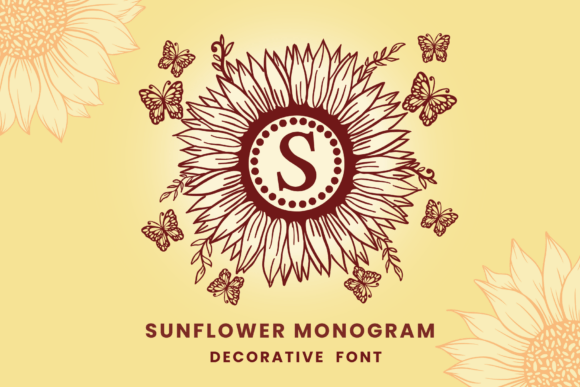
Sunflower Monogram
Mencari elemen reka bentuk yang sesuai boleh menjadi mencabar, tetapi Sunflower Monogram menawarkan koleksi luar biasa yang menaik taraf karya anda serta-merta.
Dicipta dengan ketepatan, Sunflower Monogram menyediakan vektor yang bersih, tipografi yang licin dan lesen komersial untuk ketenangan fikiran.
Sama ada anda mencipta produk POD (Print on Demand), jemputan perkahwinan atau grafik media sosial, Sunflower Monogram amat bersesuaian.